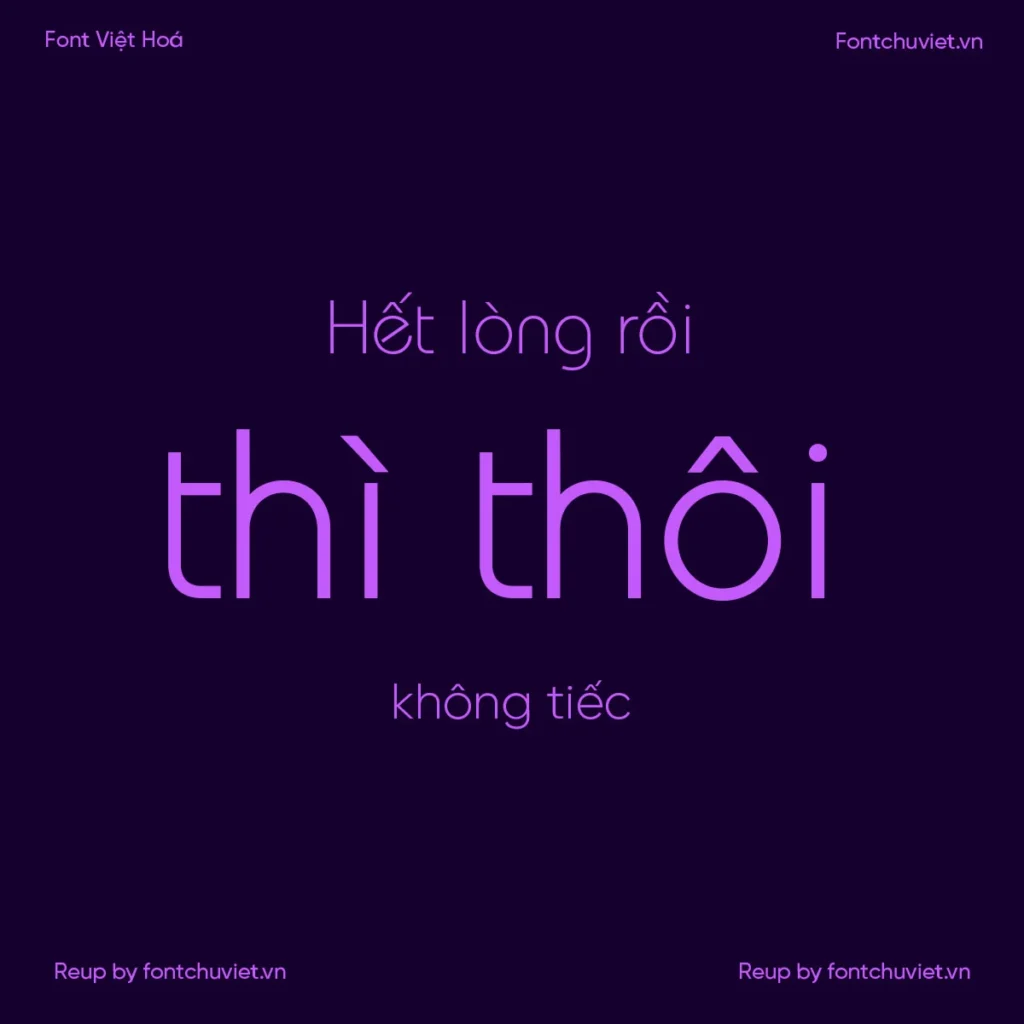
2 Font VL Bauhaus – Font Việt hoá là bộ font chữ không chân rất nổi tiếng, được Việt Linh Việt hoá, bao gồm 2 file là Regular và Light. Bộ font này rất phù hợp cho các thiết kế đồ họa, trang web và ứng dụng di động.
Giới thiệu về 2 Font VL Bauhaus – Font Việt hoá
2 Font VL Bauhaus – Font Việt hoá là bộ font chữ không chân nổi tiếng, được Việt Linh Việt hoá, bao gồm 2 file là Regular và Light. Bộ font này rất phù hợp cho các thiết kế đồ họa, trang web và ứng dụng di động.
Các tính năng của 2 Font VL Bauhaus – Font Việt hoá
Các tính năng chính
Bộ font này có các tính năng chính như sau:
- Không chân
- Phù hợp cho các thiết kế đồ họa, trang web và ứng dụng di động
Các lợi ích
Bộ font này mang lại các lợi ích như sau:
- Tăng tính chuyên nghiệp cho thiết kế
- Phù hợp cho các thiết kế đồ họa, trang web và ứng dụng di động
Kết luận
2 Font VL Bauhaus – Font Việt hoá là bộ font chữ không chân rất nổi tiếng, được Việt Linh Việt hoá, bao gồm 2 file là Regular và Light. Bộ font này rất phù hợp cho các thiết kế đồ họa, trang web và ứng dụng di động. Hãy tải xuống và sử dụng bộ font này ngay hôm nay!